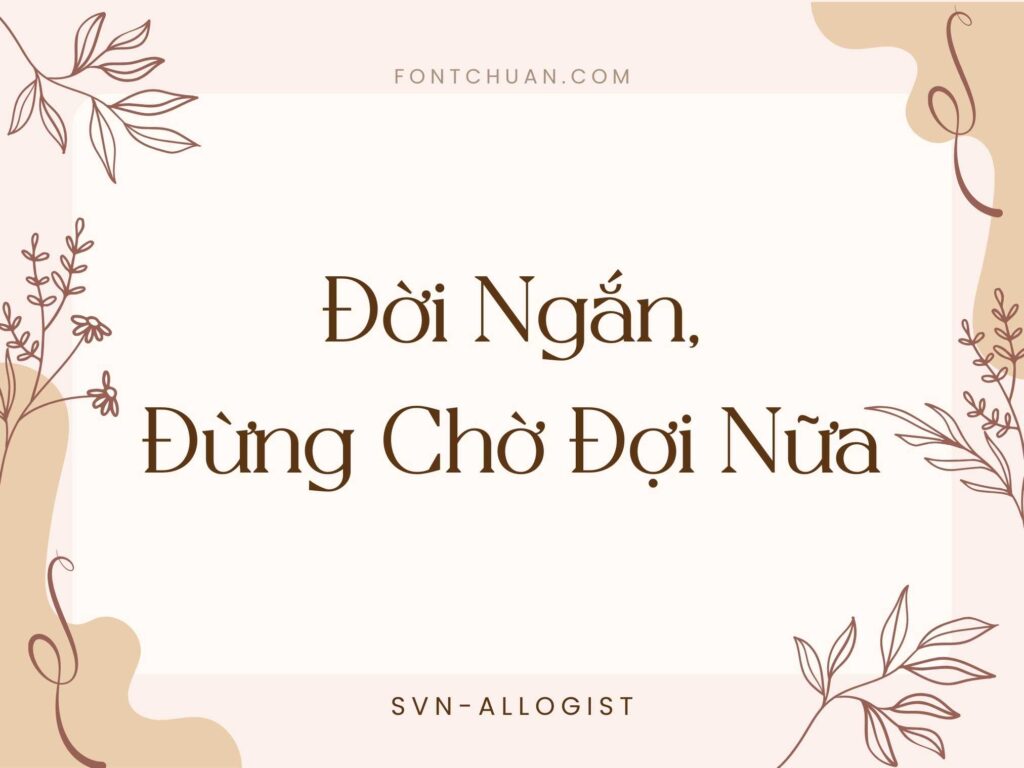
Font SVN Allogist Việt Hóa
Tác giả Font: Dora Typefoundry
Allogist là một font chữ hiện đại được thiết kế bởi Dora Typefoundry, mang phong cách sang trọng và tinh tế. Font này có đường nét mềm mại nhưng vẫn giữ được sự mạnh mẽ, phù hợp cho nhiều mục đích sử dụng như thiết kế logo, tiêu đề, ấn phẩm quảng cáo, bao bì sản phẩm và thời trang. Với hơn 200 ký tự hỗ trợ đa ngôn ngữ, Allogist là một lựa chọn lý tưởng cho các nhà thiết kế muốn tạo ra những tác phẩm chuyên nghiệp và sáng tạo. Font đã được Việt hóa để hỗ trợ tiếng Việt bởi Styleno.1 Fonts, đồng thời hỗ trợ nhiều ngôn ngữ khác, giúp mở rộng phạm vi sử dụng trên toàn cầu. Font này được thành viên của Font Chuẩn sưu tầm và chia sẻ, đáp ứng nhu cầu của bạn đọc và ứng dụng thực tế vào các dự án thiết kế.
Đặc điểm thiết kế của Allogist bao gồm cấu trúc chữ cân đối, đường nét mềm mại nhưng vẫn giữ được sự mạnh mẽ và thu hút. Font này phù hợp cho các ứng dụng như thiết kế logo, nhãn hiệu, bao bì sản phẩm, tiêu đề sách và áp phích. Các ngành nghề phù hợp bao gồm quảng cáo, thương hiệu, thời trang và thiết kế sáng tạo.